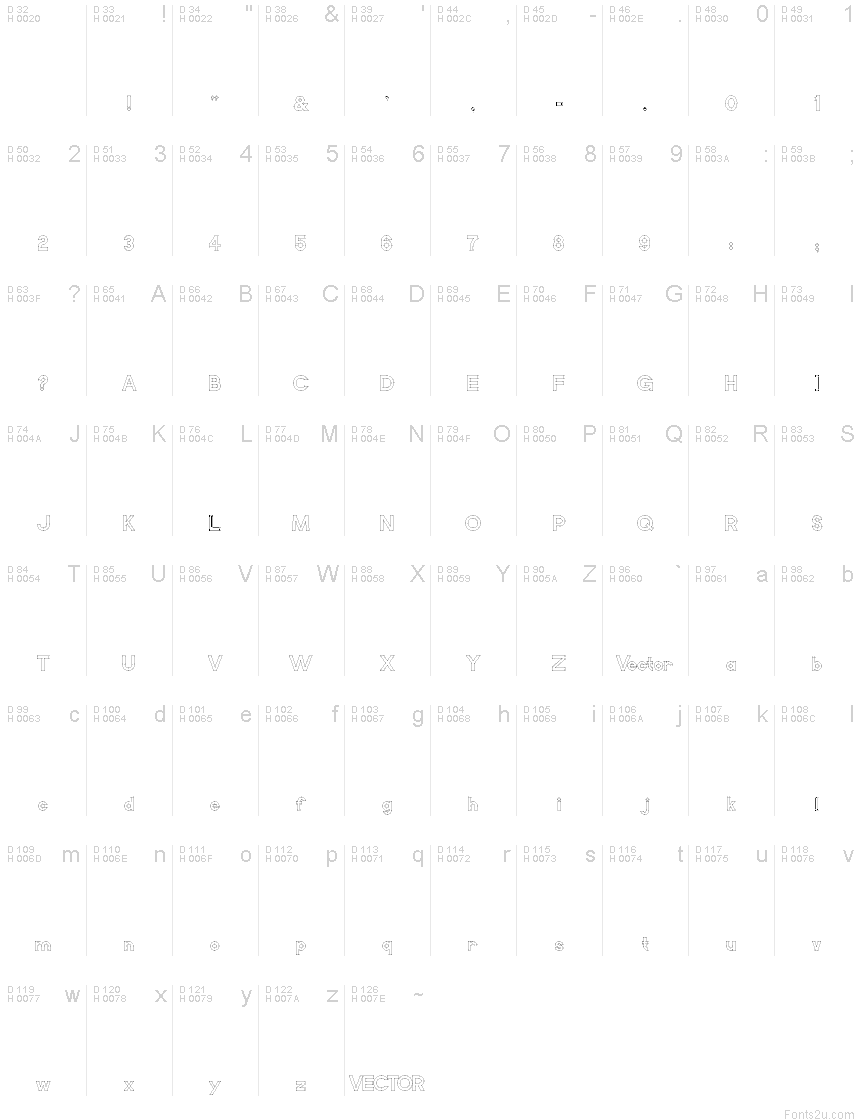
Vector، من تصميم J.F.Y. Daniel Gauthier من GautFonts، هو خط تقني مفرغ (Outline) مجاني يتميز بمظهر حاد كأنه مرسوم على الشاشة. تجمع الحروف بين حرف V حاد وواسع مع منحنيات دائرية تقريبًا وحرف t مقطع بأسلوب معياري، مما يجعل التصميم يبدو كمسارات متجهة (Vector paths) نظيفة تحولت إلى حروف.
يتناسب هذا الخط بشكل طبيعي مع شعارات الألعاب، ومنشورات الموسيقى الإلكترونية، وشاشات بدء التطبيقات، وأغلفة الخيال العلمي، وعناوين الموشن جرافيك حيث يمكن لخط مجاني أن يضفي لمسة خفيفة وتخطيطية. استخدمه عندما تريد أن تعطي الكلمات القصيرة أو الأحرف الأولى طابعاً رقمياً وتخطيطياً بدلاً من الطابع الثقيل، حيث تحافظ الخطوط الخارجية المفتوحة على مظهر هوائي مع الحفاظ على هندسة صارمة.